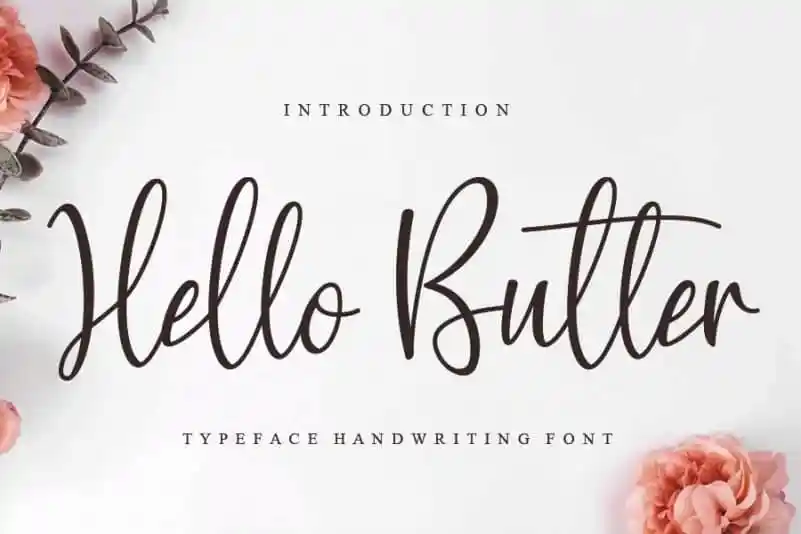
Hello Butter Script Font – Download Grátis
Essa fonte de calligrafia é uma criação especial do Designer creativeletter, criada para oferecer experiências únicas e distintas aos seus usuários. A Hello Butter Script Font não apenas adicionará um toque autêntico e elegante ao seu design gráfico, mas também lhe dará a sensação de explorar novos territórios do mundo da tipografia. Com linhas levemente onduladas que se estendem em uma mistura perfeita de seriedade e delicadeza, esta fonte é ideal para trabalhos de design que exijam um ar refinado ou elegante. Ela pode ser usada para destacar títulos de página inteira, criar identidades visuais memoráveis ou até mesmo decorar mensagens amigáveis nas redes sociais. Englobe a arte da escrita com uma fonte que tem tanto charme quanto espírito criativo. Descubra o prazer e a riqueza de experiência que este design original pode lhe proporcionar.